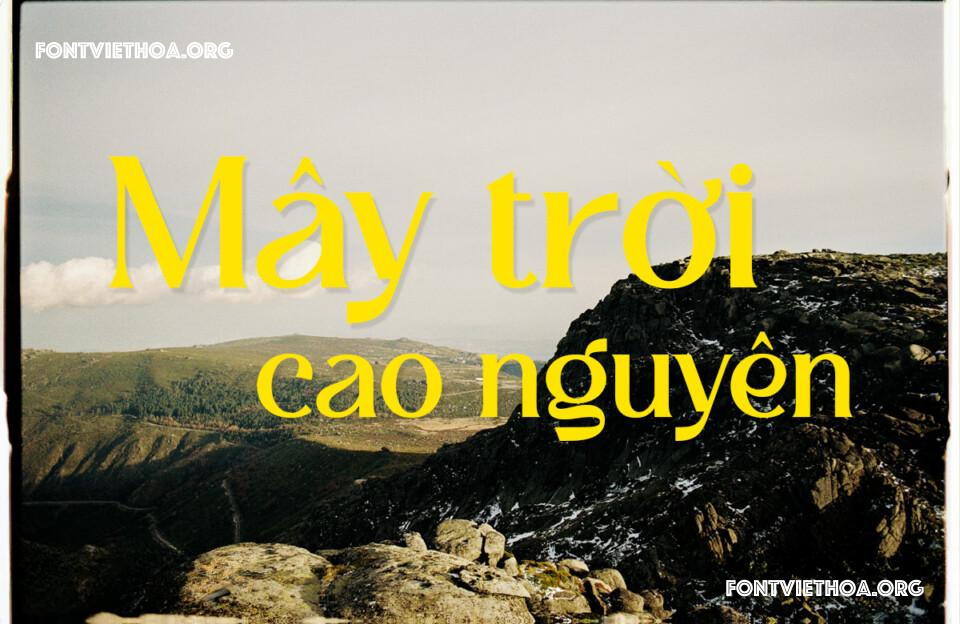
Tên font: Font Việt hóa VIP Riuka
Tác giả: Burhan Afif
Font Việt hóa VIP Riuka
Font Việt hóa VIP Riuka là một trong những font chữ được yêu thích nhất trong thiết kế tạp chí. Với thiết kế chữ tròn và chân nổi bật, font này mang lại một vẻ ngoài đẹp và sang trọng cho các ấn phẩm.